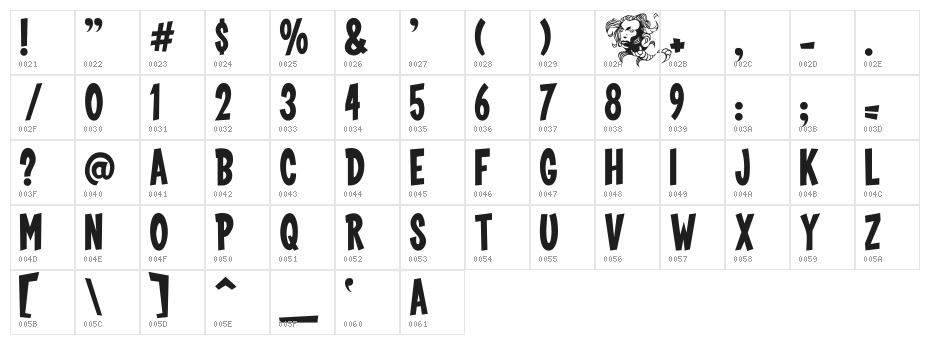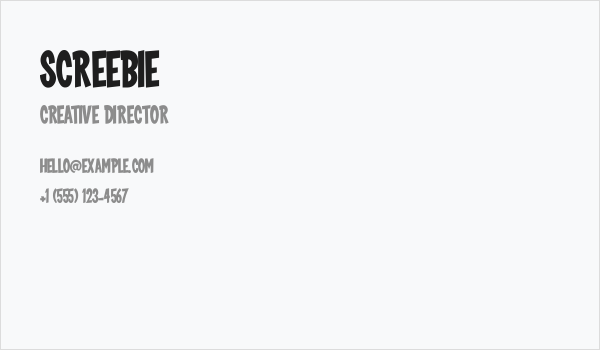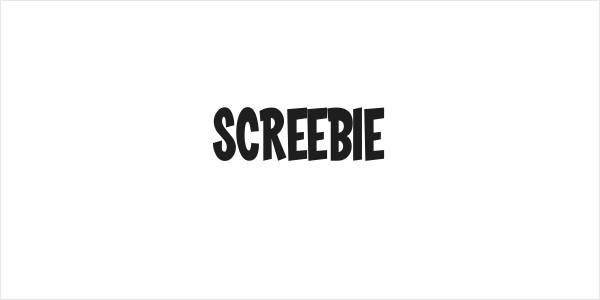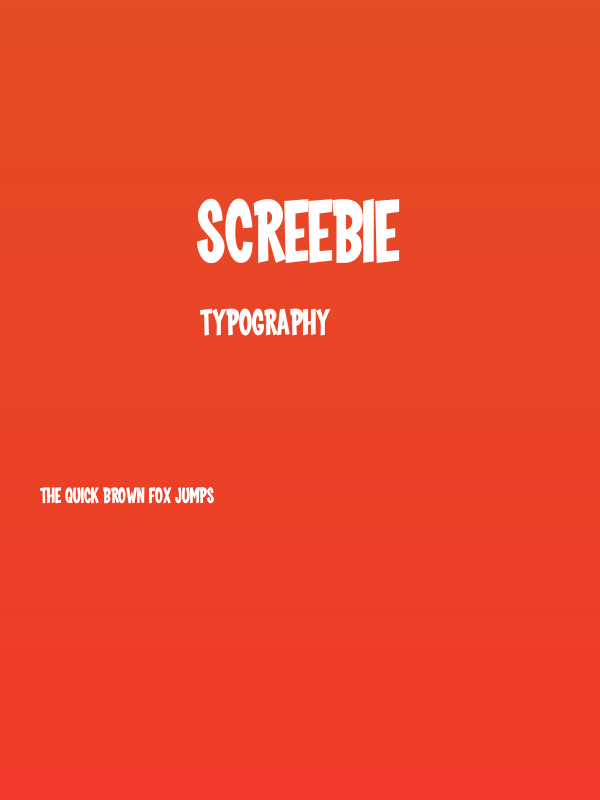
Screebie Font
| Style général | Playful, Creative |
| Cas d'utilisation | Headlines, Posters, Creative Projects |
| Projets proposés | Ideal for posters, comic books, children's books, and any creative project needing a bold, fun aesthetic. |